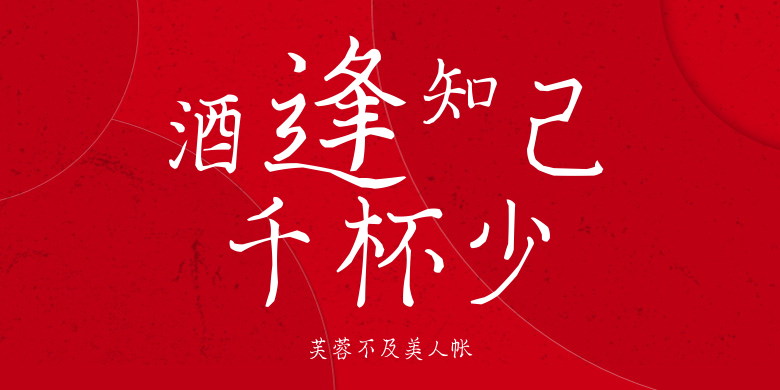
芙蓉不及美人帐
芙蓉不及美人帐,这款字体结构工整、笔画清晰,兼顾美观与易读性,适用于标题、正文、海报、包装、LOGO 等多种场景。字形优雅稳定,风格百搭耐看,适配日常排版与创意设计,让文字呈现更舒适、更具质感。芙蓉不及美人帐一笔一画,皆是细节,以均衡的比例、流畅的线条打造舒适视觉体验,字形端正大气,风格简约现代。无论是商业设计、品牌宣传还是日常排版,都能轻松驾驭,让文字更有格调与力量。芙蓉不及美人帐字体下载。